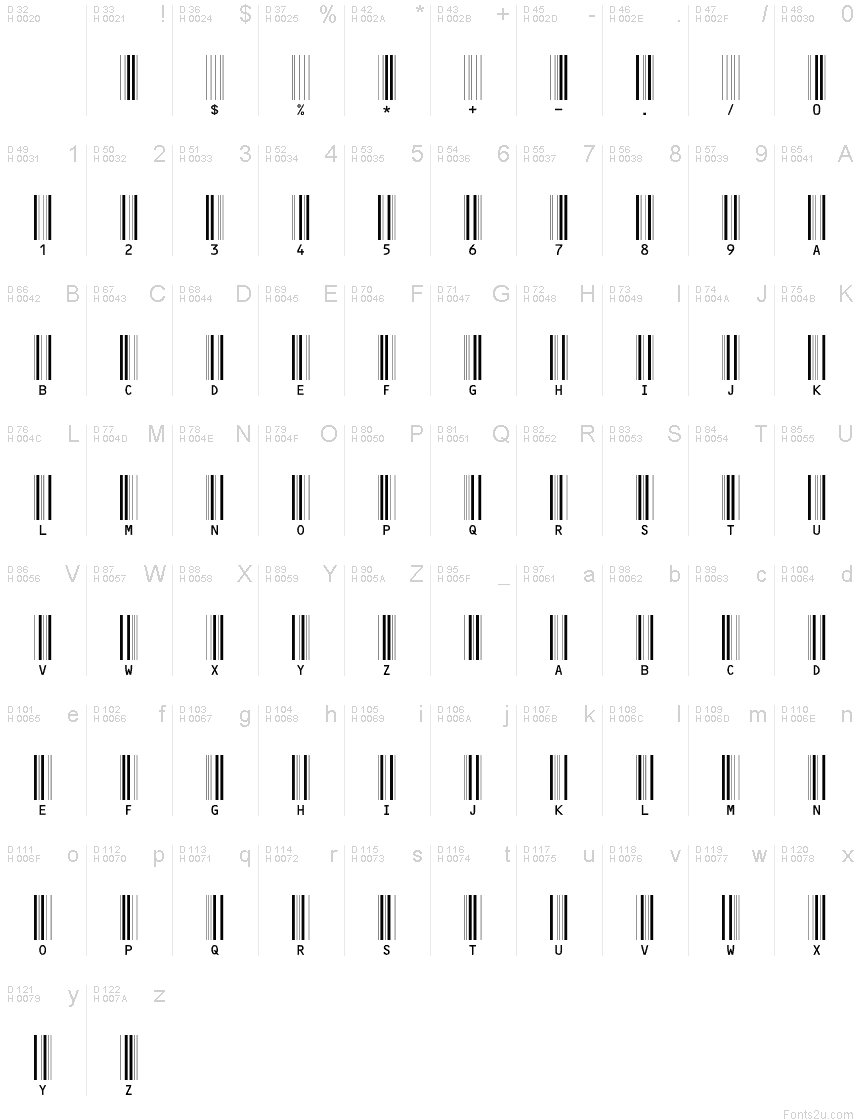
C39HrP24DhTt von Bear Rock Technologies Corp. ist ein kostenloser Barcode-Font, der einfache Textzeichen in präzise, maschinenlesbare Striche im klassischen Code-39-Stil verwandelt. Die Balken wirken sauber und funktional, mit großzügigen Abständen, die auch bei schnellen Ausdrucken mit niedriger Auflösung für zuverlässige Scans sorgen.
C39HrP24DhTt eignet sich hervorragend für Inventaretiketten, Versandaufkleber, Lagerplatzbeschriftungen, Asset-Sticker, Preisschilder, Eintrittskarten, Bibliothekssysteme und Projekte, die Scanner erfordern. Setzen Sie die Schrift etwas größer als den Fließtext und lassen Sie genügend Freiraum um den Code herum; kombinieren Sie diesen kostenlosen Font für die für Menschen lesbare Zeile darunter am besten mit einer sachlichen serifenlosen Schrift.